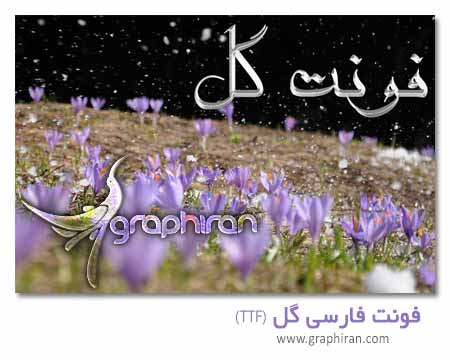
دانلود فونت های حرفه ای انگلیسی Exans و Tua با طراحی هندسی
دو فونت انگلیسی حرفه ای و بسیار زیبا را برای شما در این پست آماده دانلود کرده ایم که از ابتکاری ترین فونت های انگلیسی مناسب طراحی لوگو می باشند. این دو فونت زیبا که دارای طراحی هندسی می باشند با نام Tua و Exans به صورت حرفه ای منتشر شده اند و شما می توانید آنها را به صورت رایگان از گرافیران دانلود کنید. طراحی بی نظیر این فونت های جدید انگلیسی در نوع خود بی نظیر می باشند. امیدواریم این فونت های جذاب انگلیسی مورد پسند شما طراحان گرافیک قرار گیرند.
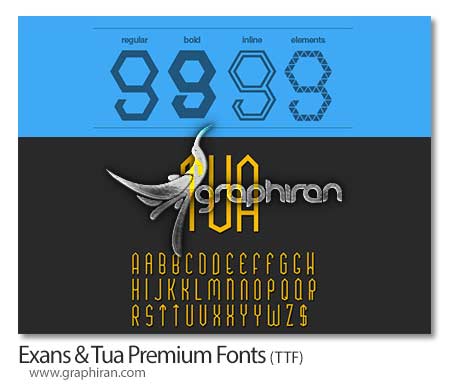فونت انگلیسی حرفه ای
دانلود فونت فارسی گرافیکی فرزیان A Farzian Farsi Font
فونت فارسی فرزیان یکی از جدیدترین فونت های گرافیکی فارسی با طراحی بی نظیر می باشد که مطمئنا مورد پسند بسیاری از طراحان گرافیک قرار خواهد گرفت. این فونت فارسی زیبا که دارای دو خط در پایین و بالای حروف است برای انواع طراحی گرافیکی می تواند کاربرد داشته باشد. با استفاده از استایل های مناسب می توانید زیبایی این فونت جدید فارسی را دو چندان کنید. می توانید این فونت را در ادامه مطلب به صورت رایگان دانلود کنید.
فونت فارسی فرزیان
دانلود فونت فارسی افسانه A Afsaneh Farsi Font
فونت افسانه یکی از جدیدترین و زیباترین فونت های فانتزی فارسی می باشد که می تواند در موادر مختلفی مورد استفاده قرار گیرد. طراحی زیبای این فونت رایگان فارسی از ویژگی های آن بوده و سلیقه های مختلف را به خود جلب خواهد کرد. استفاده از آن با استایل های زیبا می تواند تاثیر چشم گیری در طراحی گرافیکی شما داشته باشد. مانند همیشه می توانید این فونت زیبا را در ادامه مطلب دانلود کنید. امیدواریم این فونت جدید و فانتزی فارسی مورد پسند شما واقع شود.
فونت افسانه
دانلود فونت فارسی سلامت A Salamat Farsi Font
فونت فارسی سلامت یکی از زیباترین فونت های فارسی با ظاهری ساده در عین حال بسیار کاربردی می باشد. این فونت جدید فارسی مطمئنا برای انواع طراحی گرافیکی برای گرافیست ها و طراحان مورد استفاده خواهد بود. مانند همیشه می توانید این فونت فارسی زیبا را در ادامه مطلب دانلود کنید.
فونت فارسی سلامت
دانلود فونت فارسی گل A Gol Farsi Font
فونت فارسی گل یک فونت جدید فارسی با طرحی زیبا قابل استفاده برای طراحان و گرافیست ها می باشد. این فونت فارسی زیبا که می تواند برای طراحی مذهبی نیز مورد استفاده قرار گیرد یکی از زیباترین فونت های فارسی گرافیکی می باشد. طراحی هنری این فونت فارسی زیبا از ویژگی های منحصر به فرد است فونت است. امیدواریم این فونت فارسی جدید مورد پسند شما قرار گیرد. در ادامه مطلب می توانید این فونت را دانلود کنید.
فونت فارسی گل
دانلود فونت فارسی سردار هور A Sardar Hoor Font
فونت فارسی سردار هور از دیگر فونت های فارسی گرافیکی زیبا می باشد که می تواند کاربرد فراوانی در انواع طراحی داشته باشد. این فونت برای بزرگداشت شهید علی هاشمی ساخته شده است. شما مانند همیشه می توانید در ادامه مطلب این فونت فارسی زاویه دار را دانلود و استفاده کنید.
فونت سردار هور
دانلود فونت فارسی جدید همّت A Hemmat Farsi Font
سعی کرده ایم در گرافیران نمونه های زیبا و متعددی از فونت های فارسی را برای شما گردآوری کنیم. در این پست فونت فارسی همت را آماده کرده ایم که یکی از فونت های زیبای فارسی به شمار می رود. طراحان و گرافیست های محترم می توانند با استفاده از این فونت در طرح های گرافیکی خود، زیبایی آن را چند برابر کنند. در ادامه مطلب با دانلود این فونت جدید فارسی با همراه باشید.
فونت فارسی همت